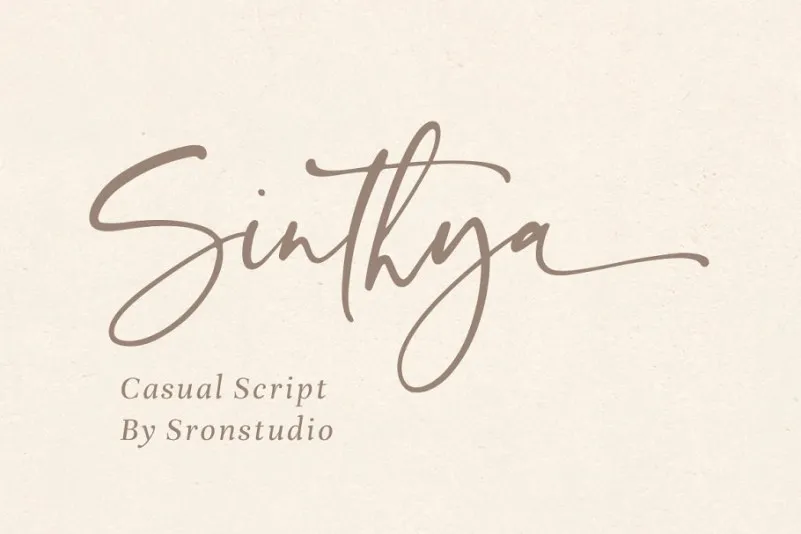
Sinthya Script Font – Download Grátis
Sinthya Script Font é uma elegante fonte escrita à mão que oferece um toque sofisticado para seu projeto. Ela combina influências dos xilografos caius e estilo de escrita manual, criando um design perfeito tanto para logotipos quanto para postais, embalagens de produtos, fotografias, avisos e qualquer outro tipo de arte digital que você possa imaginar. Com suas letras maiúsculas e minúsculas completas, alongamentos e finalizações em swashes no alfabeto minúsculo e símbolos multilíngues incluídos, Sinthya é uma opção perfeita para qualquer necessidade de design. Além disso, seus números e pontuação são fornecidos na fonte também, tornando-a ainda mais versátil. Idealmente projetada por Zziplex, o designer que criou a fonte, Sinthya é ideal tanto para designers de marca quanto para profissionais de marketing digital. Suas linhas fluidas e sua escrita natural garantem que seu design possa se destacar em qualquer formato – seja um logotipo sofisticado para uma marca ou uma assinatura única no papel, Sinthya tem algo a oferecer aos designers gráficos amantes da arte do texto.